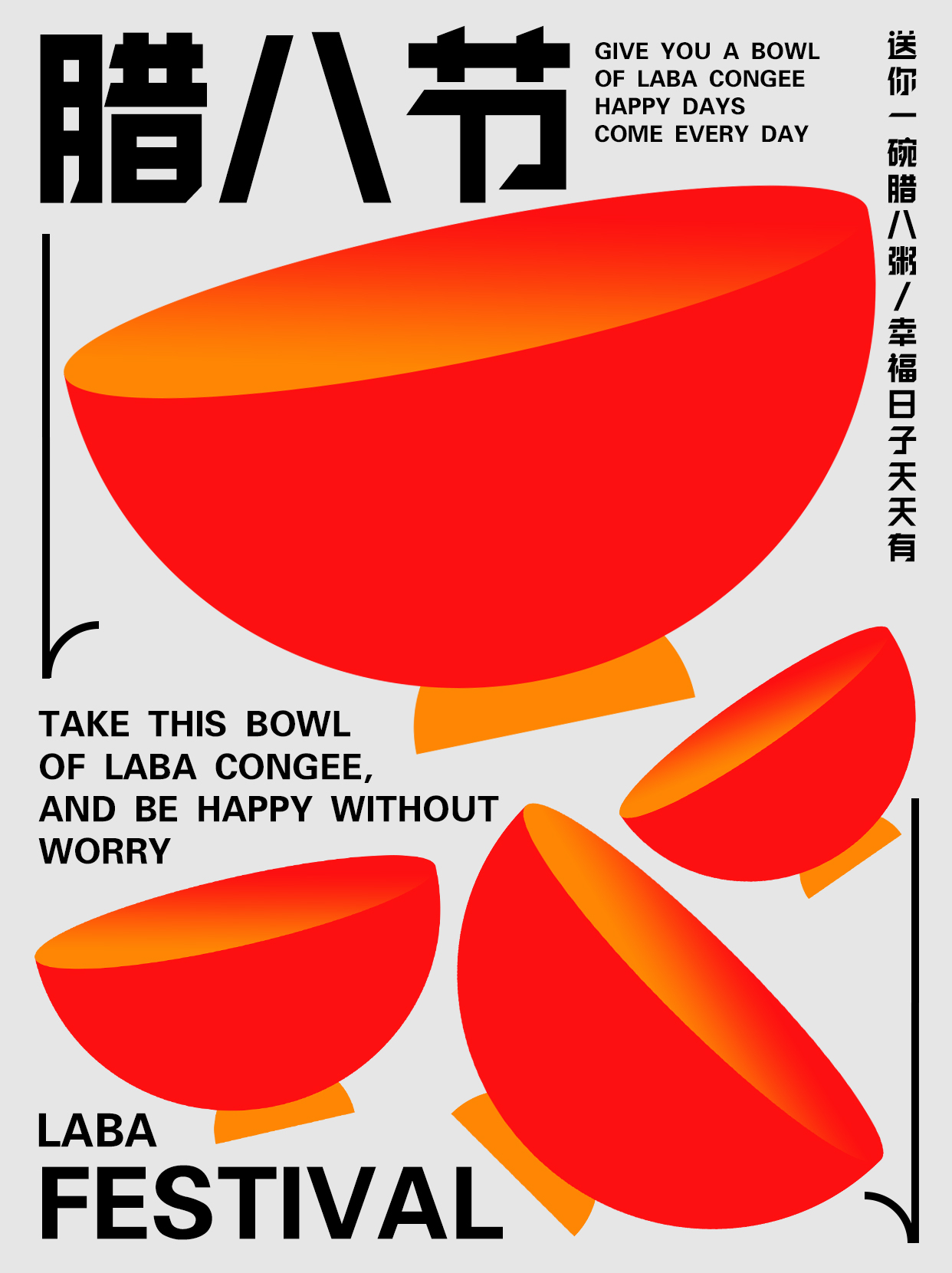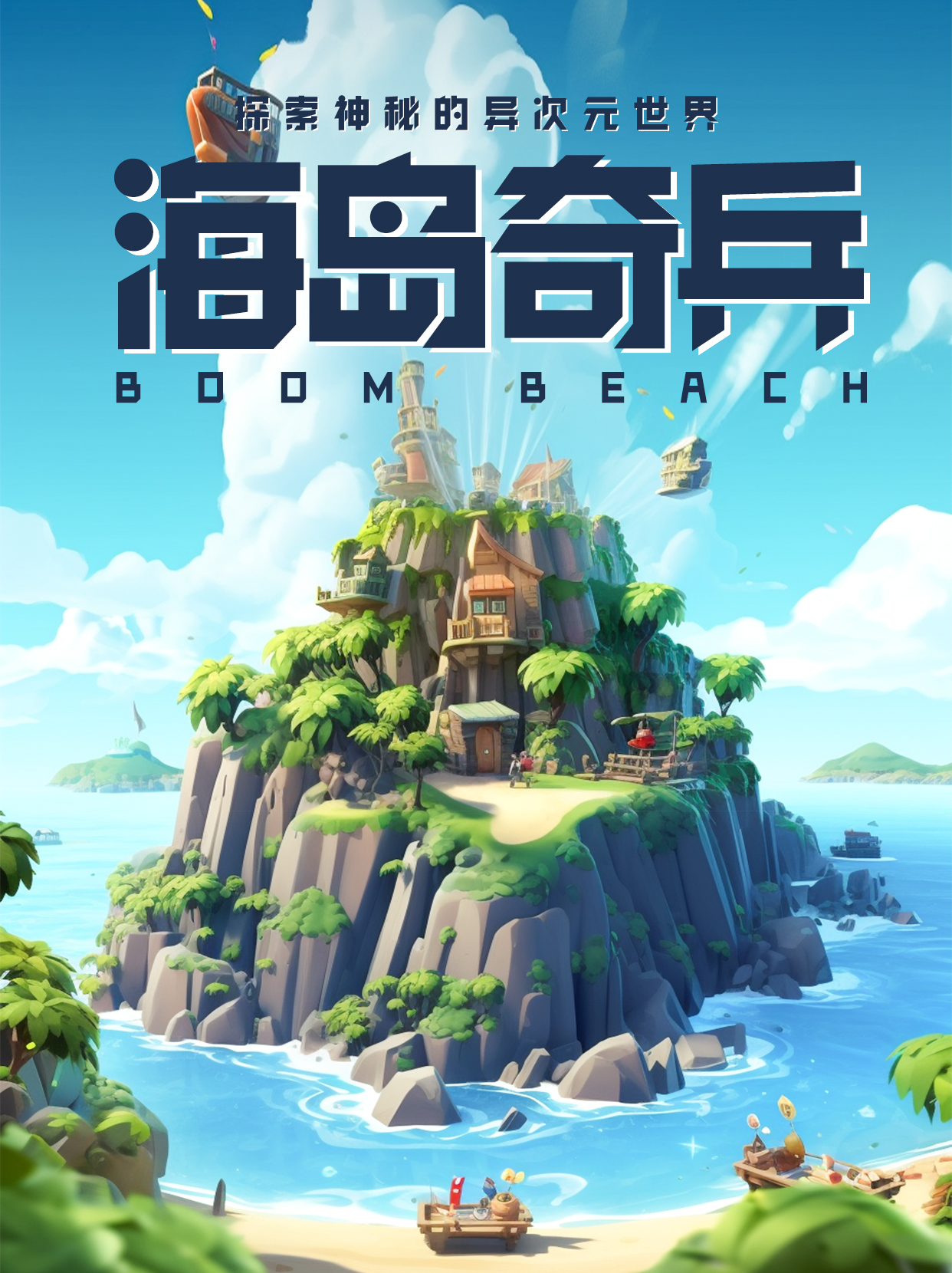
锐字洪荒之光简 大黑
REEJI-HongGuangGB Bold
锐字洪荒之光简 大黑
简体
黑体
大黑(Bold)
锐字洪荒之光简 中黑
永
锐字洪荒之光简 粗黑
永
锐字洪荒之光简 大黑
永
锐字洪荒之光简 特黑
锐字洪荒之光是一款非常适合海报的标题字,简单、直接、粗重有力,拥有四款字重满足不同需求。